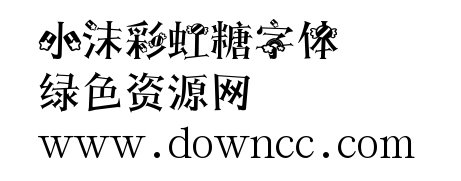
小沫彩虹糖字體是一款有著可愛糖果修飾的藝術卡通字體,給文字帶來更多的樂趣和童真,適合一些兒童主題、創(chuàng)意海報、趣味文字內容的使用,讓你的藝術設計更加出彩!
彩虹糖字體歪斜有序,大小適中,字體整體結構緊湊,既工整又大氣,可以應用于廣告設計、名片設計、包裝印刷、產品設計等應用!
小沫彩虹糖字體看似是常見的美術字體,實則增加了有趣的糖果圖案,因此而得名,兼具了藝術字體和廣告字體的特色,讓人眼前一亮,給你的設計增加更多獨特魅力!
小沫彩虹糖字即漢儀小康美術體!